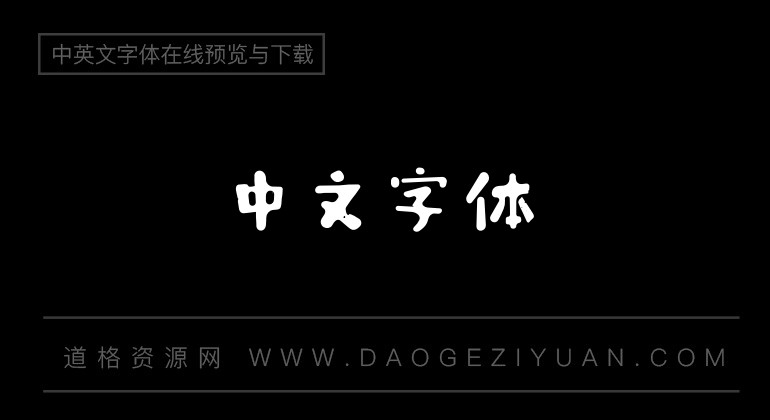
海派腔调奶油简字体是一款拥有海派特色的毛笔字体,由深圳市毛笔字设计师黄晓艳先生设计,拥有海派腔调的温柔,曲线优美,笔画柔和,结构清晰,更具有古典的美感,让人看起来更加温柔、柔和。文件名:HaiPaiQiangDiaoNaiYouJian-2.otf
海派腔调奶油简是一款非常不错的手写艺术字体,具有很好的视觉感,适合于文化类的宣传设计、商业类品牌的广告和产品包装设计以及个性化文字排版等较多场景。